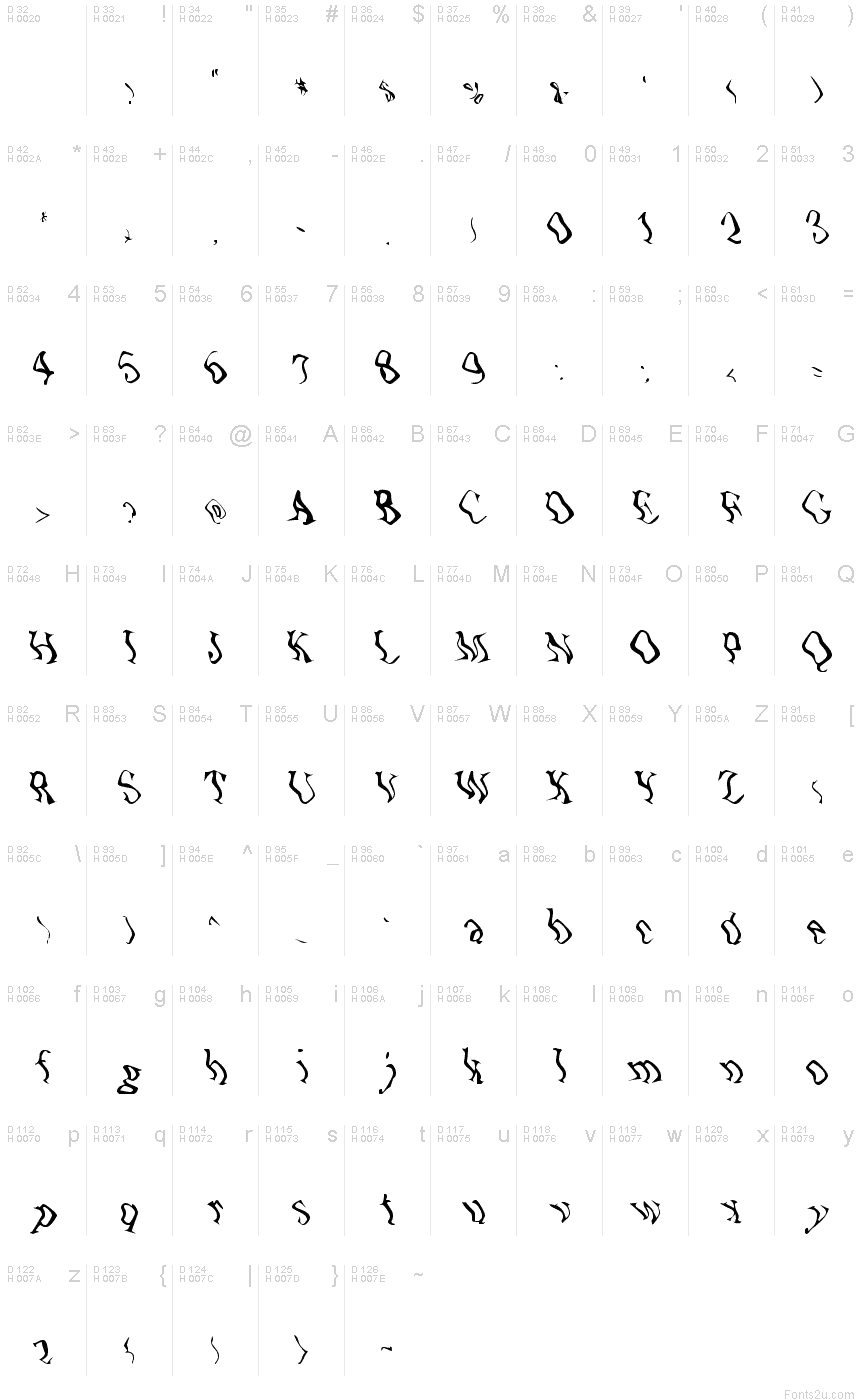
Zone23 UnderWater od Zone23 Original je bezplatné display písmo s efektem podvodní deformace a jemným nádechem blackletteru. Písmena se ohýbají a kroutí, jako byste se na ně dívali pod hladinou; díky háčkovitým tahům a měkkým, nepravidelným křivkám působí font tekutě, nikoliv drsně.
Hodí se na plakáty, klubové letáky, loga her, obálky zinů nebo na grafiku akcí s tajemnou atmosférou, kde potřebujete bezplatný font, který vyvolá mokrý, nestabilní dojem i s minimem textu. Použijte ho pro krátké nadpisy, titulní karty nebo monogramy – zdeformované siluety a náznak starých stylů udělají největší parádu v krátkých a úderných kompozicích.